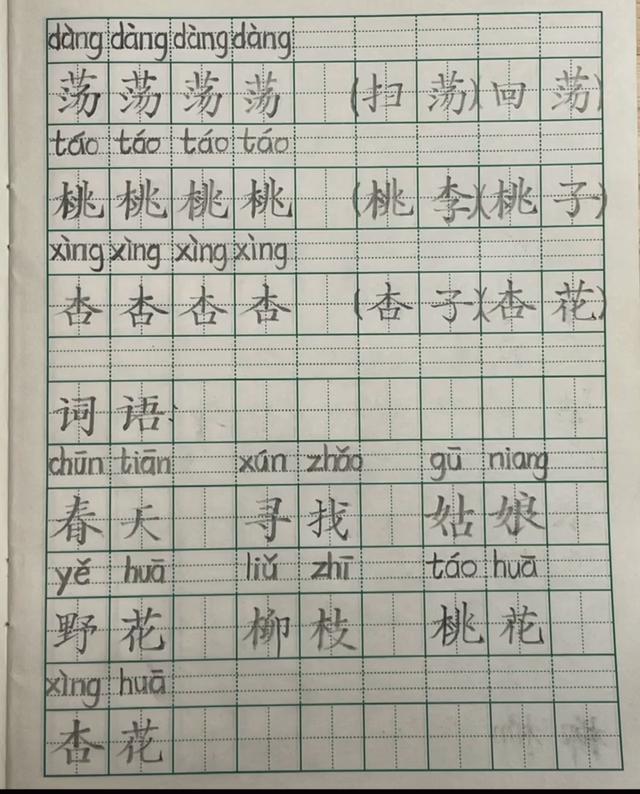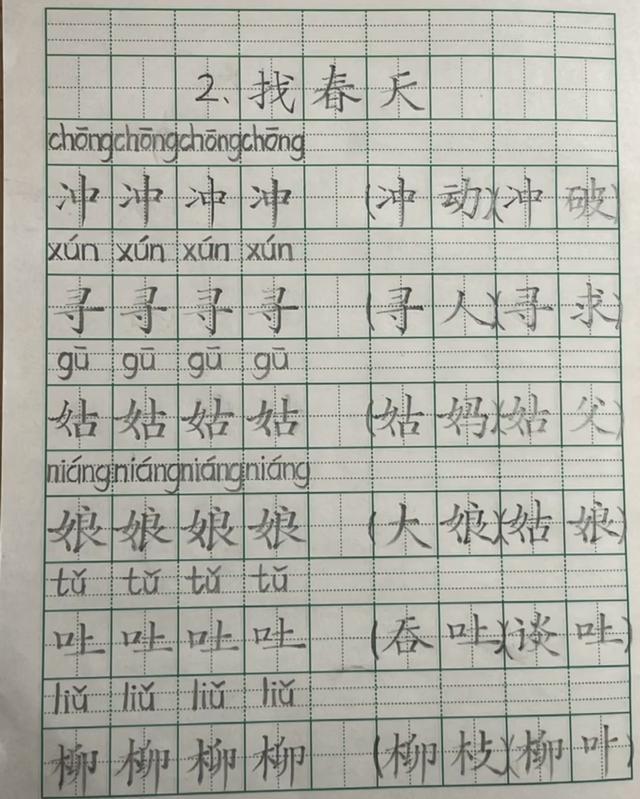
家长晒二年级学霸预习作业,字迹堪比“神仙字体”,老师羡慕不已
眼瞅着就有开学了,很多家长在做好后勤工作的同时,也在督促孩子做好新学期开学的预习工作,对于过来人都知道,预习是学习的前提,也是学好习的前提,为此,很多同学都在这一方面下了一番功夫,不仅对文章进行了细读、分段,书写段落大意,而且还对生字词进行了提前书写,这不,就有家长晒出了二年级学霸的预习作品,字迹工整美观,严谨大方,堪比“神仙字体”,在家长群里得到了广泛传播,成为家长传阅的焦点,连老师都羡慕不已,下面就让我们一同来欣赏一番吧。
从这位二年级学霸的字迹上看,这绝对是一位练家子,二年级还处于小学阶段的初级阶段,很多孩子在书写上还是问题,甚至写出来的字迹不堪入目,而这位二年级学霸的字迹,却颠覆了我们的认识,每一笔,每一画,每一个字都写得饱满多姿,而且堪比“印刷体”一般,不仅仅是工整规范,而且还写出了书法“范”,书法味道十足,很有功底,至少在书法上也是练习过的,一上眼就让人感觉到与众不同,倘若在考试中写出这样的字迹,想必,连阅卷老师都不忍心多扣分。
这位二年级学霸的字迹,在用笔上以方笔为主,笔笔见方,写出了不一样的韵味,而且对硬笔书法的手写技巧是非常娴熟的,同时能够在平日里得到应用,这就是一项能力,而点画之间还有明显的照应关系,安排得十分紧凑,相互之间能够体现出一种顾盼生情,首尾相接的韵味,真是别致清新,难怪能够成为家长传阅的焦点,这绝对是一种实力,不容置疑。
看到这样的字迹,很多家长都不敢相信,这样的字迹竟然出自一位二年级学生之手?颠覆了我们对二年级学霸的认识,这样的字迹恐怕连很多成年人都难以为之,可是在他的笔下却写的如此轻松自如,真是印证了那样一句话,自古英雄出少年!对此,分享你的看法和见解。